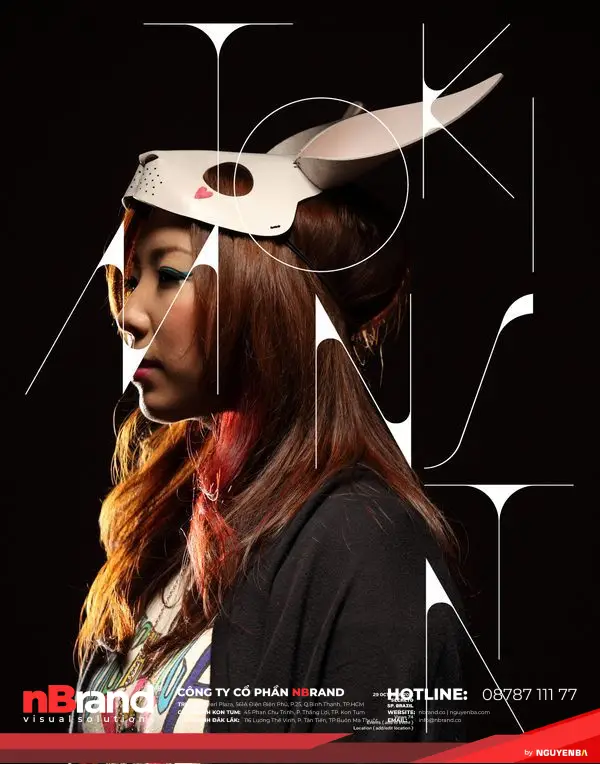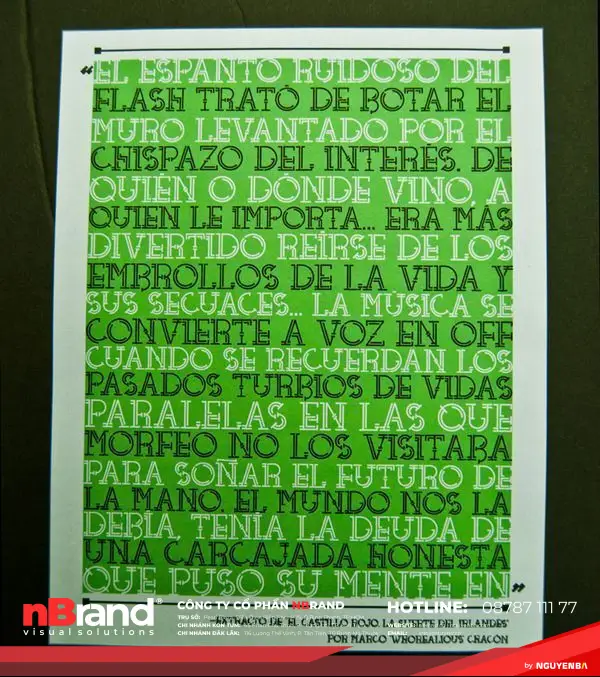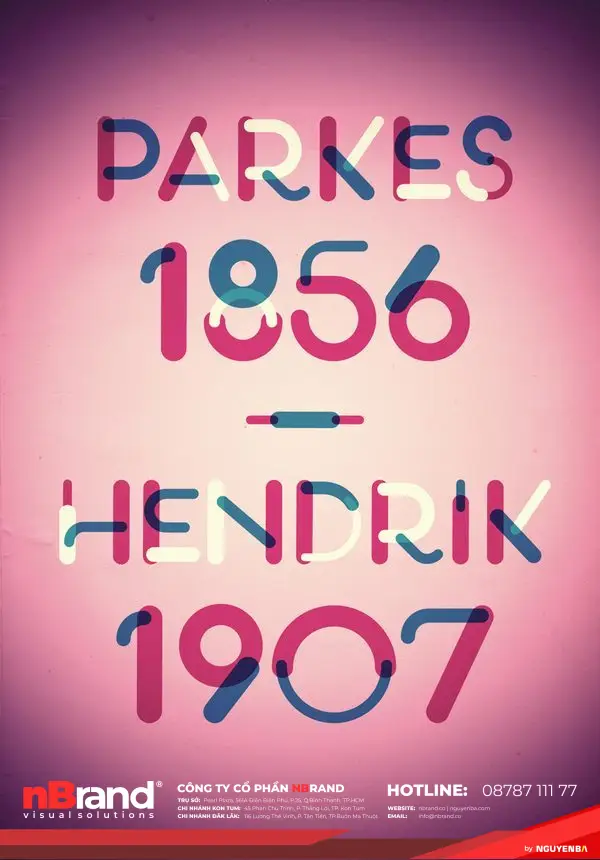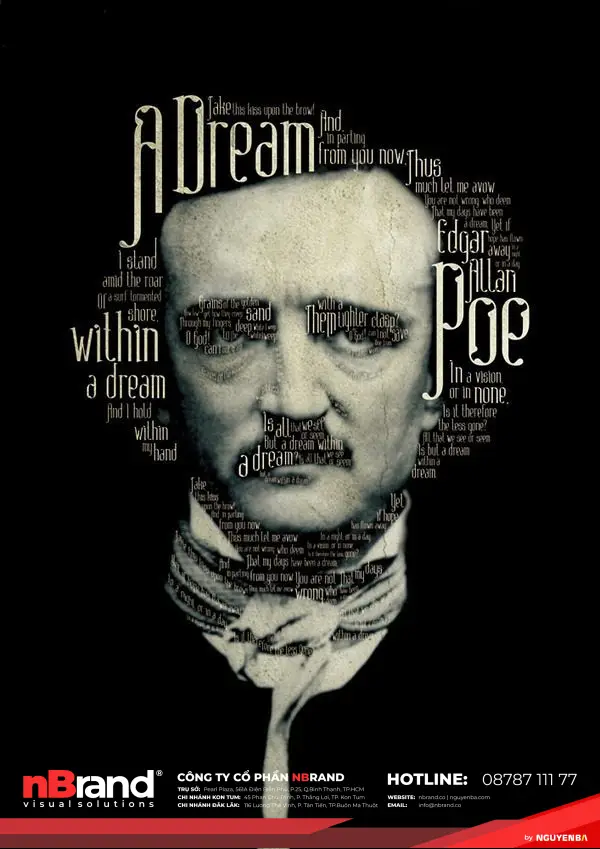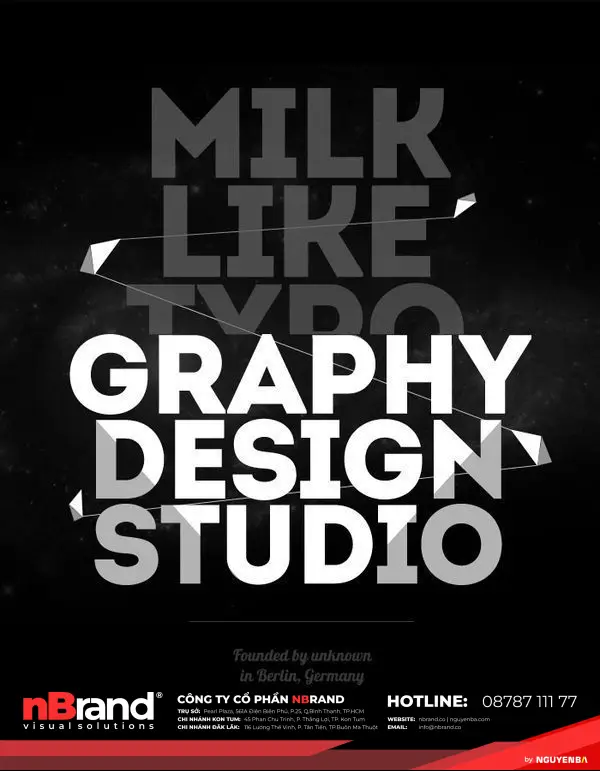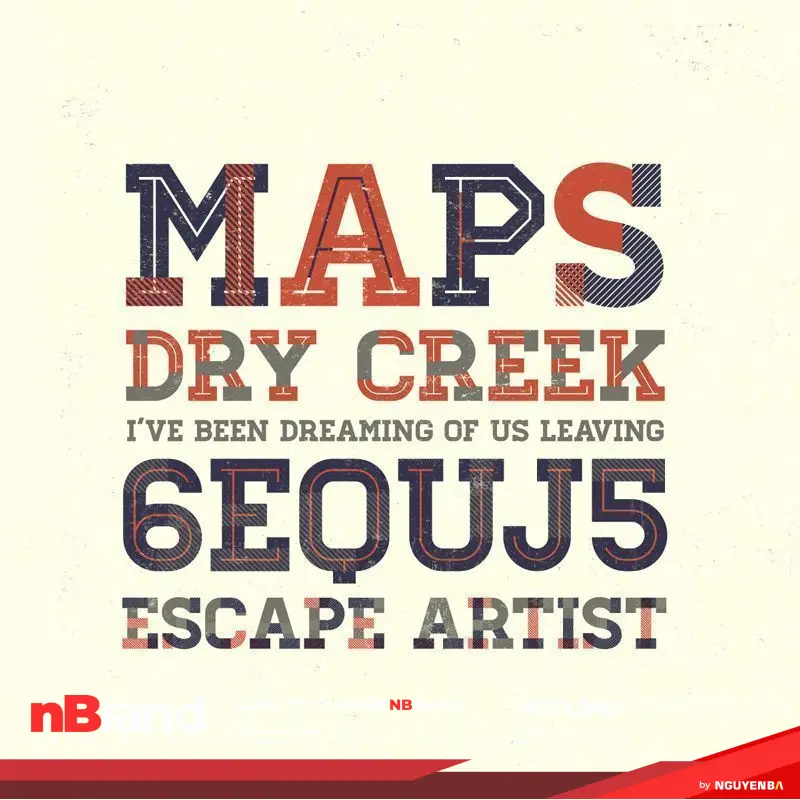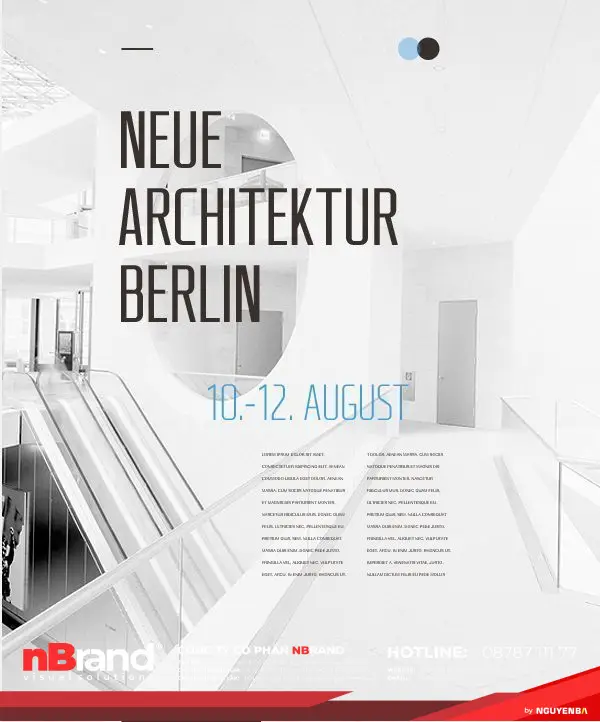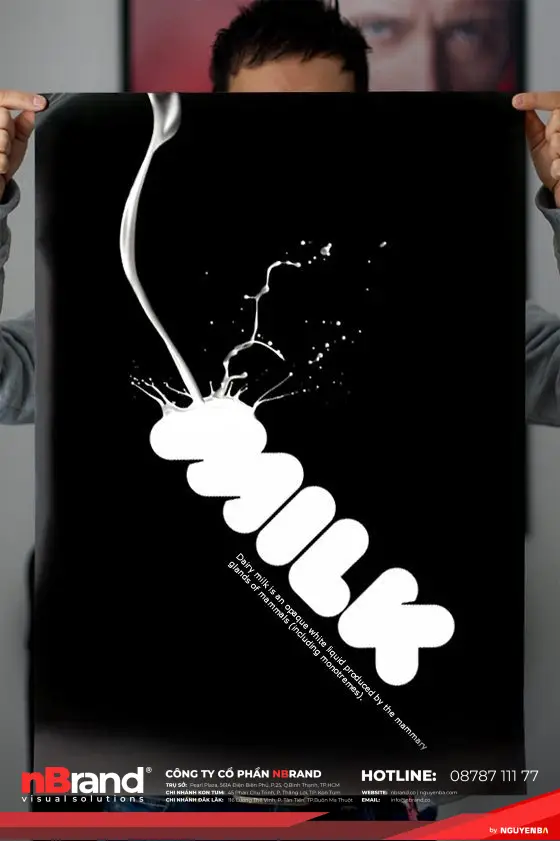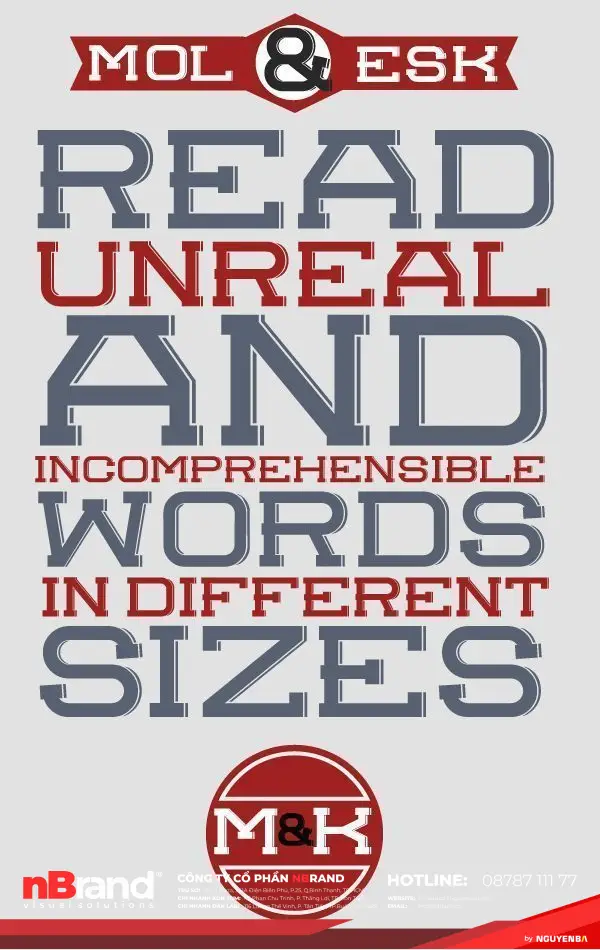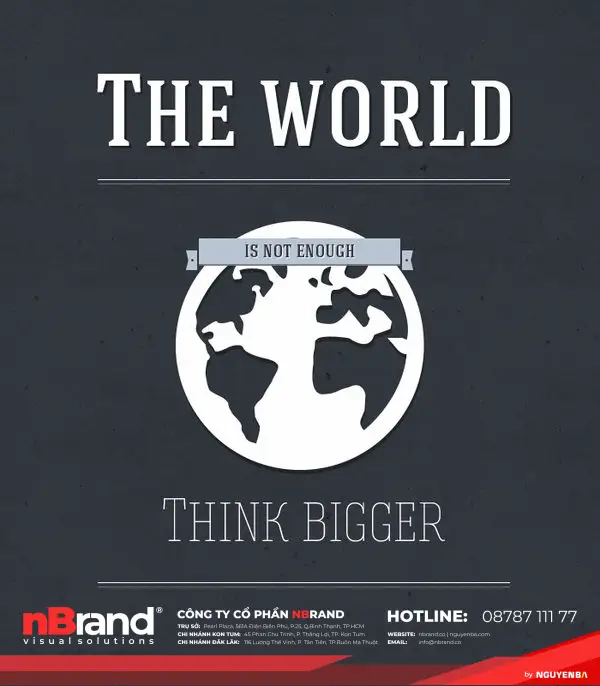
Để chọn được một font chữ phù hợp cho những dự án thiết kế là một nhiệm vụ khá gian nan bởi hiện nay có hàng ngàn font chữ tuyệt đẹp xuất hiện trên rất nhiều các trang web mà bạn có thể dễ dàng tải về và sử dụng chúng. Nếu bạn đang tìm kiếm để tạo ra một logo lớn và táo bạo cho doanh nghiệp của mình hay một dự án thiết kế poster cho một sư kiện thì hơn 20 ví dụ dưới đây sẽ mang tới nguồn cảm hứng cho bạn, chúng là một sưu tập những thiết kế sử dụng cực kỳ hiệu quả font chữ để nhấn mạnh hay thể hiện ý đồ của nhà thiết kế trong tác phẩm của mình. Điểm chung của hơn 20 thiết kế này đó là thay vì sử dụng hình ảnh, chúng lại sử dụng font chữ làm chủ đạo, làm điểm nhấn trong mỗi thiết kế. Bộ sưu tập này bao gồm rất nhiều phong cách đa dạng, từ cổ điển cho tới sự đơn giản, thanh thoát.
NEO DECO
Neo Deco là một bộ font chữ đẹp và chuyên nghiệp, nó được tạo ra để phục vụ cho việc thiết kế logo. Trong tác phẩm này, bộ font chữ được sử dụng rất đơn giản, thanh thoát và lại mang lại một cảm giác thật sự phong cách cho tác phẩm.
PLSTK
PLSTK là một bộ font chữ hoàn toàn độc đáo. Nó là sự kết hợp của các chi tiết cơ khí trong mỗi ký tự để làm cho các thiết kế sử dụng PLSTK trở nên nổi bật giữa đám đông. Đây là bộ font chữ yêu thích của rất nhiều nhà thiết kế khi họ cần tạo ra một cái gì đó khác biệt.
ACCENT
Accent cũng là là một font chữ đặc biệt khác, nó mỏng, sắc nét và nhìn thật ấn tượng trong các thiết kế poster, điển hình là tấm poster bên dưới. Font chữ này đặc biệt ở chỗ nó có rất nhiều các khoảng trống trong mỗi nét chữ, điều này giúp cho Accent là sự lựa chọn hoàn hảo cho những tấm poster bởi sự kết hợp của những bức ảnh phía sau cùng nghệ thuật typography luôn là một cách hay để thể hiện ý tưởng.
KABEL
Kabel là một font chữ được thiết kế tốt. Nó trở nên tuyệt vời nhất là khi được sử dụng kết hợp cùng với các hiệu ứng ánh sáng và các bộ phối màu, tấm ảnh bên dưới là 1 ví dụ trong cách sử dụng hiệu quả bộ font chữ này.
KILOGRAM
Kilogram là một bộ font chữ dày, đậm và hoàn hảo nếu bạn sử dụng trong các dòng tiêu đề hay một biểu ngữ cần tạo ra một sự ảnh hưởng nhất định.
CODE
Code là một bộ font chữ rất đẹp, đơn giản và thanh thoát. Các đường nét mảnh tạo sự cuốn hút cho bộ font này và sẽ rất hữu dụng nếu bạn cần thể hiện một cái gì đó chuyên nghiệp và rõ ràng.
TELEFONO
Telefono là một bộ font chữ khá độc đáo, nó thêm vào các chi tiết cho mỗi ký tự. Bộ font này sẽ hữu ích cho các thiết kế poster hay thiết kế logo bởi những ký tự với nhiều chi tiết luôn mang tới sự tò mò.
NOVECENTO
Novecento là một bộ font chữ đơn giản, bộ font này rất đa dạng từ loại cực kỳ mảnh cho đến cực kỳ đậm. Vì vậy nó mang tới sự linh hoạt trong việc sử dụng, từ những tiêu đề cho đến các thiết kế logo hay chỉ đơn giản là chữ viết thông thường, nó cũng rất phù hợp khi xuất hiện trên các tấm poster.
HAGIN
Nếu bạn đang tìm kiếm một bộ font chữ để dòng tiêu đề của mình trở nên nổi bật thì Hagin là một sự lựa chọn tốt. Bộ font này có chân chữ đổ bóng, đậm và vô cùng hấp dẫn.
MOLESK
Molesk là một bộ font chữ lớn 3D, nó thích hợp với các thiết kế sử dụng nhiều ký tự. Nó không rõ ràng như một số bộ font chữ khác nhưng nó sẽ rất tuyệt vời để làm cho thiết kế của bạn trở nên khác biệt.
PARANOID
Paranoid là một trong những bộ font chữ được yêu thích nhất bởi nó có một thiết kế rất đẹp và hoàn toàn khác biệt. Bộ font chữ này là hoản hảo cho các thiết kế cần sự nổi bật, nó không phải là font chữ dễ đọc nên nó phù hợp hơn để thể hiện các tiêu đề ngắn gọn hơn là các dòng văn bản dài chứa nhiều thông tin.
VAL
Val là một font chữ nhìn khá vui vẻ và hài hước. Có một vài điều cần nhớ khi sử dụng bộ font chữ này: Sử dụng tất cả các chữ là chữ thường để có được hiệu ứng nghiêng và nó không thể hiện tốt khi sử dụng ở kích thước nhỏ. Val là font chữ hoàn hảo cho nghệ thuật thiết kế logo sử dụng typography, điển hình là bức ảnh phía bên dưới.
ABSINTHE
Nếu đang tìm kiếm một bộ font chữ cổ điển thì Absinthe có lẽ là thứ mà bạn đang cần tới. Nó là một bộ font chữ cổ điển tuyệt vời, với bộ font này bạn có thể thoải mái sáng tạo theo cách của mình và nó còn ấn tượng hơn nếu kết hợp cùng với các hiệu ứng mang phong cách cổ điển.
TETRA
Tetra là một bộ font chữ được thiết kế để xuất hiện trên các tấm poster, đặc biệt là poster cho các lễ hội hay một sự kiện. Các đường nét của bộ font rất khá vui vẻ kết hợp cùng các hiệu ứng 3D giúp Tetra phù hợp trong hầu hết các tình huống.
INTRO
Intro là một bộ font rất đẹp, rõ ràng. Nó hoàn hảo cho những thiết kế logo cần sự hấp dẫn và sắc nét.
LAVANDERIA
Lavanderia là một bộ font chữ viết tay đẹp, rất phóng khoáng và mềm mại. Bộ font này là hoản hảo khi kết hợp cùng với các sản phẩm handmade, các thiết kế cần tới sự tiếp cận của chữ viết tay.
RBNO2
RBNO2 là một bộ font chữ thanh thoát và nó mang tới cảm nhận của một sự ngăn nắp và khoa học, nó khá tương đồng với bộ font Courier New than Helvetica. RBNO2 sẽ đạt hiệu quả tốt nhất trong các thiết kế poster theo hướng mô phỏng.
NOMED
Nếu đang tìm kiếm một bộ font chữ hoàn toàn khác biệt thì chắc chắn Nomed sẽ là sự lựa chọn của bạn. Đây là bộ font chữ ra đời nhằm phục vụ cho các thiết kế logo ấn tượng hay các dòng tiêu đề siêu ngắn gọn, còn lại nó không phù hợp để làm bất cứ việc gì khác.